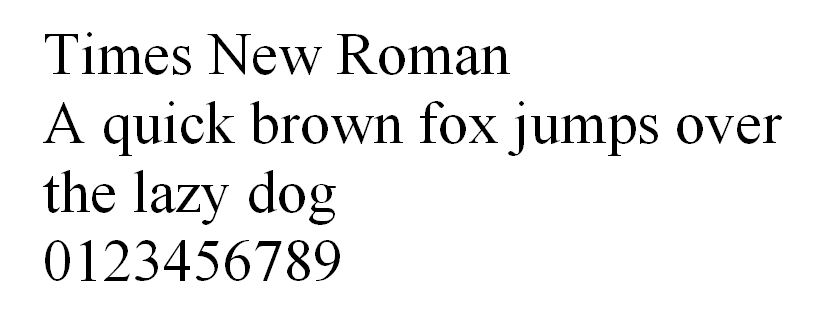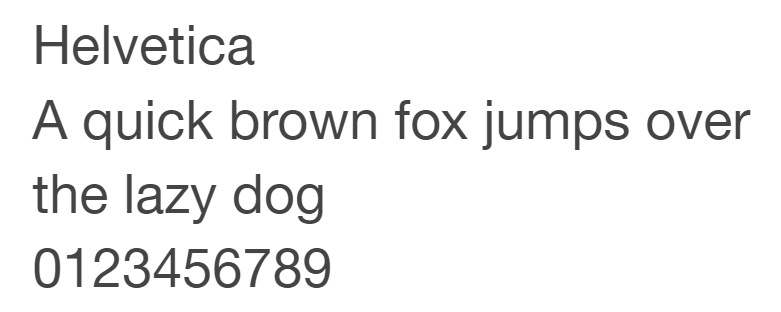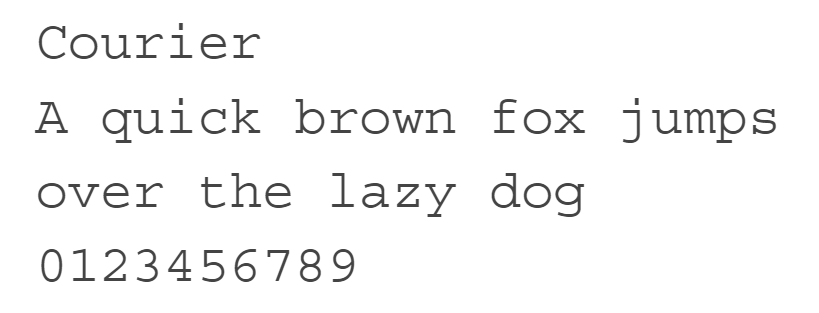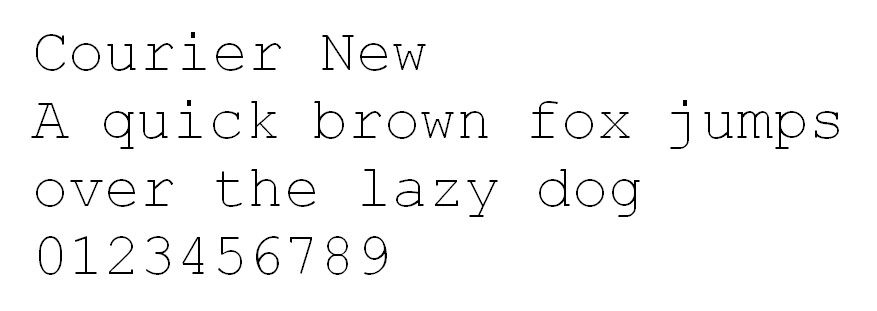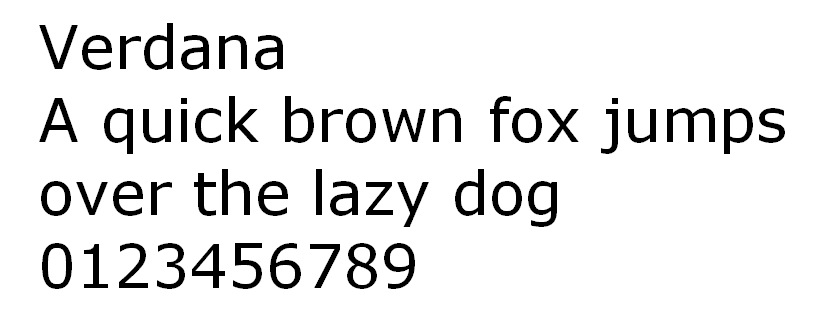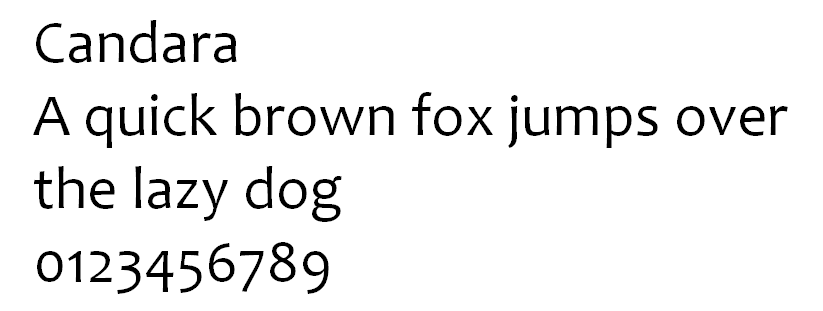
Schriftarten spielen eine große Rolle für die gesamte visuelle Wirkung einer Website. Eine sorgfältig ausgewählte Schriftart hilft, die richtige Botschaft zu vermitteln und Markenkonsistenz sicherzustellen.
Um dies zu erreichen, sollte eine hochwertige Webschriftart gut lesbar und websicher sein. Das bedeutet, dass sie auf unterschiedlichen Geräten sowie in verschiedenen Browsern und Betriebssystemen zuverlässig dargestellt wird.
Die Wahl einer geeigneten Schriftart ist jedoch nicht immer einfach. Häufig stößt man auf Schriftarten, die optisch ansprechend sind, aber nicht websicher – oder umgekehrt.
Um Sie dabei zu unterstützen, haben wir eine Liste der 20 besten HTML-Schriftarten für Ihre Website zusammengestellt.
Websichere Schriftarten sind Schriftarten, die auf den meisten Betriebssystemen vorinstalliert sind. Dadurch wird sichergestellt, dass sie beim Zugriff von unterschiedlichen Geräten und Browsern wie vorgesehen dargestellt werden.
Zu den bekanntesten Beispielen für websichere Schriftarten zählen Arial, Times New Roman und Helvetica.
In der Typografie gehört jede Schriftart zu einer von fünf Schriftfamilien, die nach ihren gestalterischen Merkmalen kategorisiert werden. Dazu zählen:
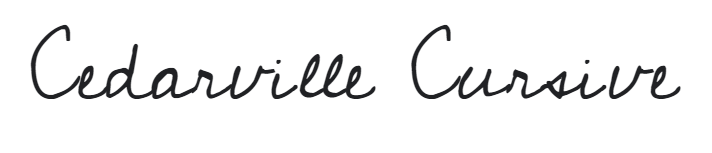
Schreibschriften ahmen Handschrift nach, wobei die Buchstaben üblicherweise in einer geschwungenen, fließenden Form miteinander verbunden sind.
Viele Menschen verbinden diese Schriftart mit Individualität, Ausdruck und Kalligrafie. Sie eignet sich daher besonders für Überschriften, Slogans und Blogtitel auf Ihrer Website, weniger jedoch für den Fließtext. Als Standardschrift eingesetzt, kann Schreibschrift schwer lesbar sein.
Die Schriftfamilie Fantasy weist in der Regel dekorative Gestaltungselemente auf, die bei jedem Buchstaben sichtbar sind. Besonders in fiktionalen Werken beliebt, können Schriftarten aus dieser Kategorie dabei helfen, ein Genre unmittelbar zu vermitteln und eine bestimmte Atmosphäre zu erzeugen.
Diese Schriftkategorie wird beispielsweise häufig in Fantasy- und Science-Fiction-Filmen wie Star Wars, Harry Potter oder Die Eiskönigin verwendet.
Das auffälligste Merkmal von Serifenschriften sind kleine zusätzliche Striche an den Enden der Buchstaben. Ursprünglich für den Tintendruck entwickelt, wird dieser Schriftstil heute häufig mit Formalität und Eleganz assoziiert.
Websites verwenden Serifenschriften überwiegend für Fließtext, da sie gut lesbar sind und das schnelle Erfassen längerer Inhalte erleichtern.
Zu den bekannten Serifenschriften zählen Times New Roman, Cambria und Garamond.
Als Gegenstück zu Serifenschriften verfügen serifenlose Schriften über keine zusätzlichen Striche an den Buchstabenenden.
Die meisten Schriftarten dieser Familie weisen gleichmäßige Breiten auf und wirken modern sowie minimalistisch. Serifenlose Schriftarten sind in nahezu jeder Größe gut lesbar und eignen sich daher sowohl für Printinhalte als auch für digitale Anwendungen.
Bei Monospace-Schriften besitzen alle Buchstaben und Symbole die gleiche Breite.
Da diese Schriftarten konsistent und leicht zu unterscheiden sind, werden sie häufig als Standardschrift für Schreibmaschinen und Computerterminals verwendet.
Im Folgenden finden Sie 20 websichere HTML-Schriftarten, die Sie auf Ihre Inhalte anwenden können.
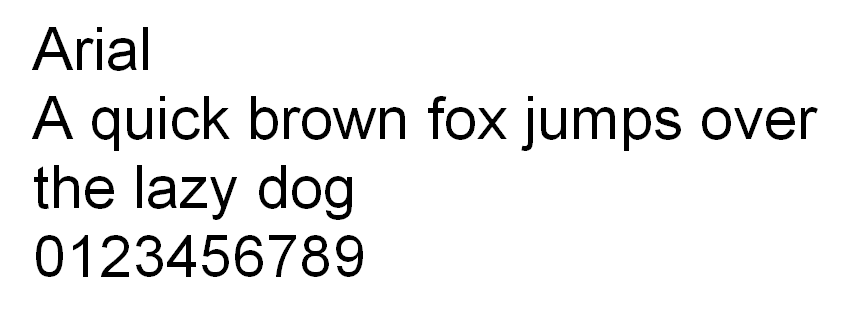
Arial ist eine vielseitige serifenlose Schriftart mit modernem Charakter. Die Buchstaben sind kräftig und stabil, was für ein klares, minimalistisches Erscheinungsbild sorgt.
Arial ist seit Langem eine feste Größe unter Bildschirmschriften, da sie in nahezu jeder Größe gut lesbar bleibt. Tatsächlich ist sie die Standardschriftart von Google Docs.
Darüber hinaus ist diese Schriftart auch in gedruckten Medien wie Zeitungen und Anzeigen weit verbreitet.
Insgesamt ist Arial eine gute Wahl, wenn Sie eine klassische Schrift suchen, die sich für die meisten Websites eignet.
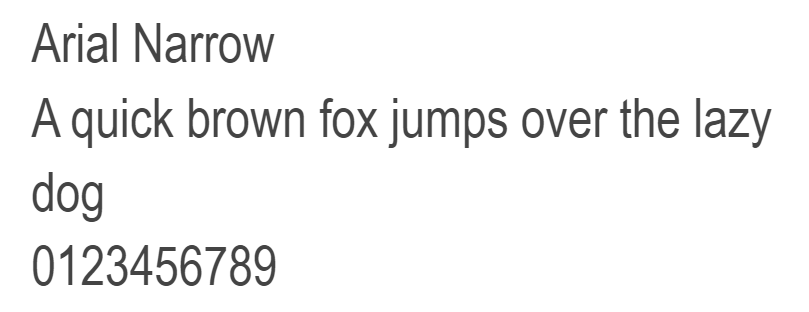
Arial Narrow ist einer von 38 Stilen der Schriftfamilie Arial. Im Vergleich zur ursprünglichen Schriftart bietet dieser Stil ein deutlich schlankeres und eleganteres Design.
Die Buchstaben wirken schmal und verdichtet, mit geringem Abstand zueinander. Das macht Arial Narrow zu einer ausgezeichneten Wahl für minimalistische Websites.
Geeignete Optionen für Schriftpaarungen sind kräftigere serifenlose Schriftarten wie Verdana und Geneva.
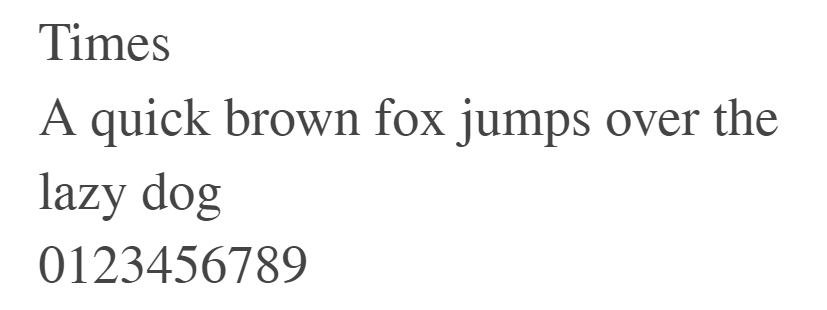
Times ist aufgrund ihres sichtbaren Kontrasts und ihres schmalen Schriftschnitts eine sehr gut lesbare Serifenschrift.
Diese Schriftart ist vielen vertraut, da sie in unterschiedlichsten Medien zum Einsatz kommt – von Büchern und Messaging-Apps bis hin zu kommerziellen Verlagsprojekten.
Ursprünglich wurde Times vor allem in gedruckten Medien wie Zeitungen verwendet und wird seitdem häufig mit Journalismus und akademischem Schreiben in Verbindung gebracht.
Daher eignet sich diese Schriftart besonders gut, um auf Ihrer Website eine vertraute und formelle Atmosphäre zu schaffen.
In diesem Artikel haben wir die 20 besten websicheren HTML-Schriftarten vorgestellt, um Ihnen die Auswahl zu erleichtern. Eine kurze Zusammenfassung einiger Optionen:
Beachten Sie, dass jede Schriftart einen eigenen Charakter besitzt. Wählen Sie daher eine Schrift, die sowohl gut lesbar ist als auch zur Identität Ihrer Marke passt.